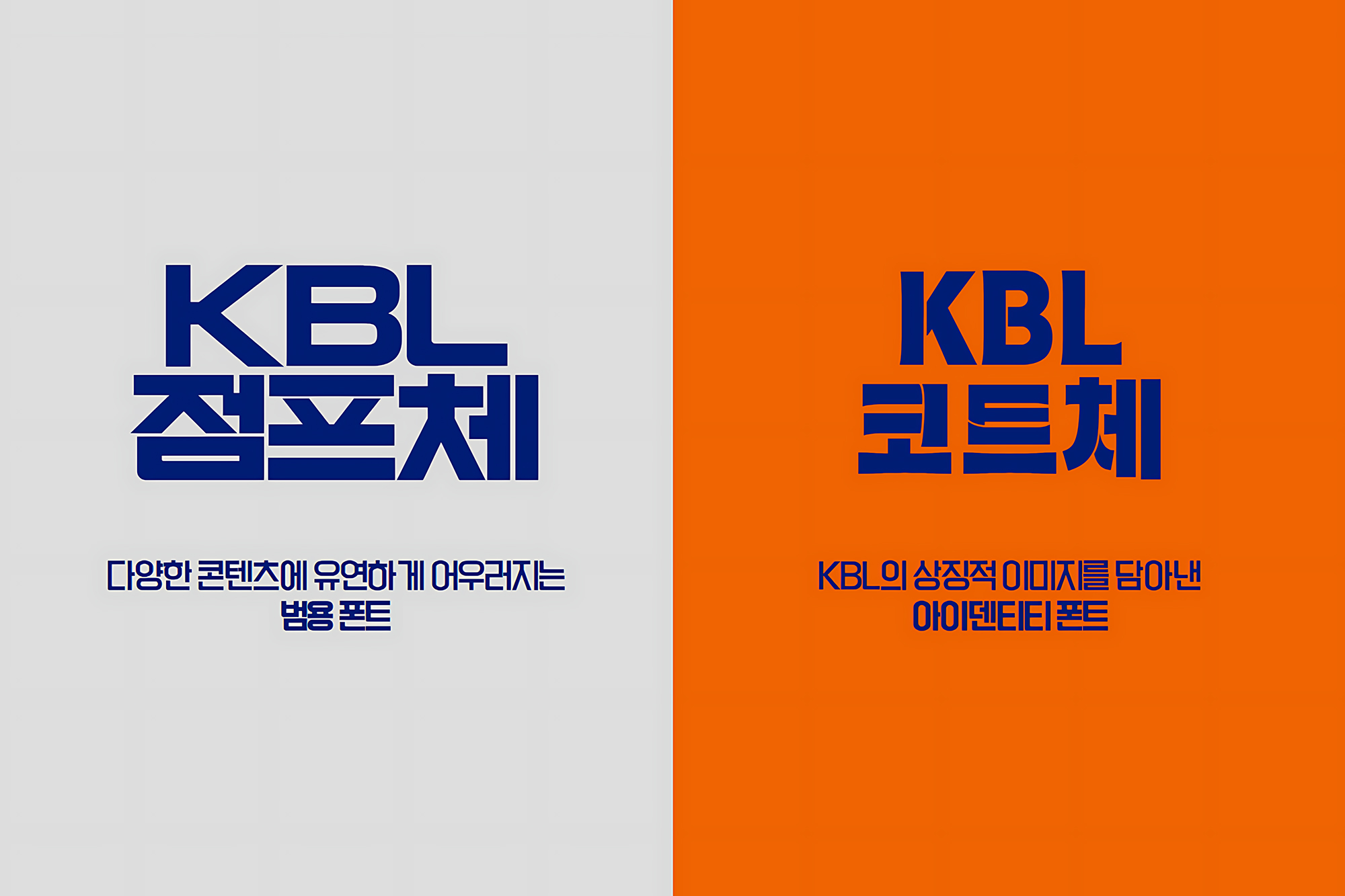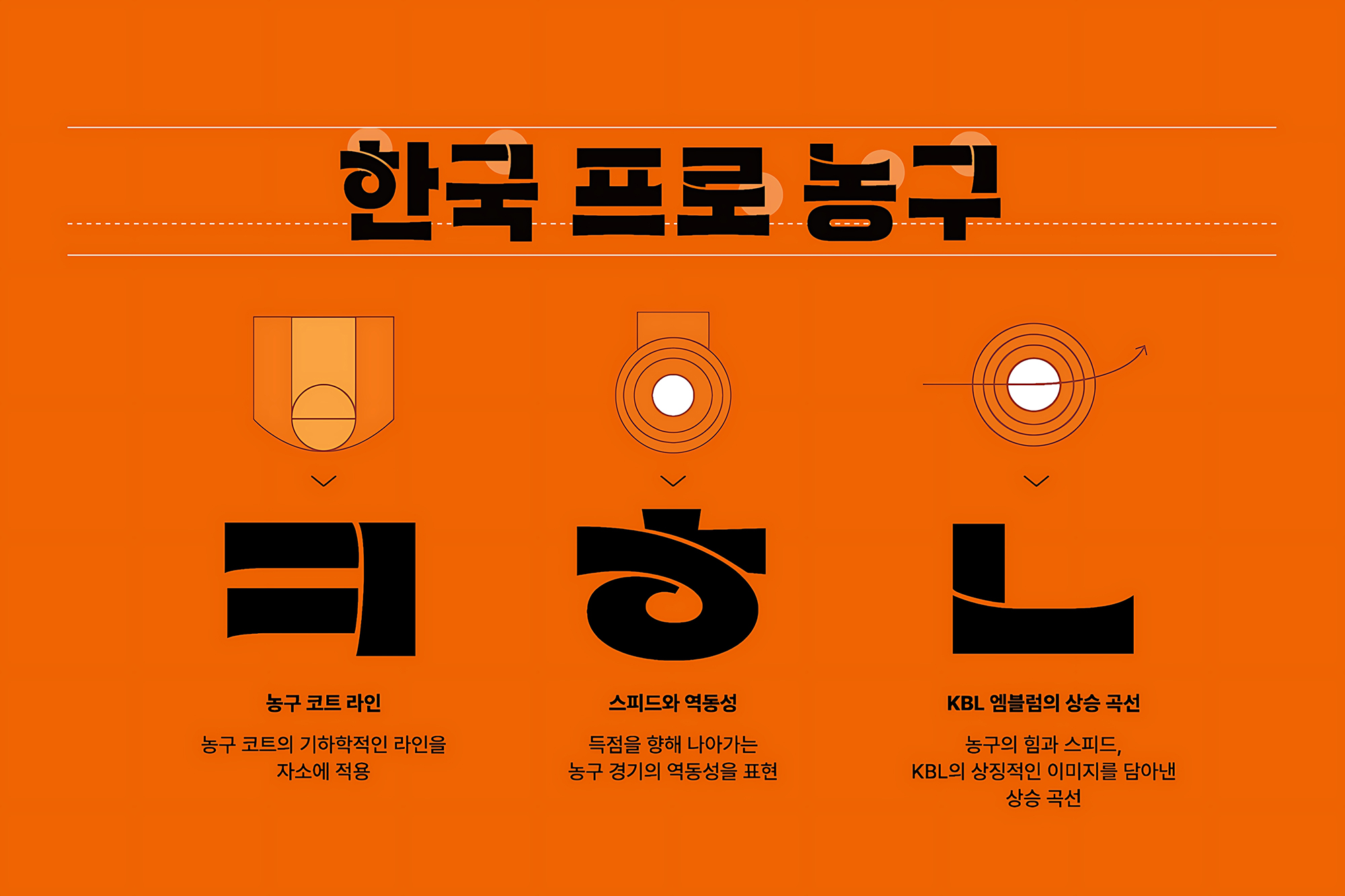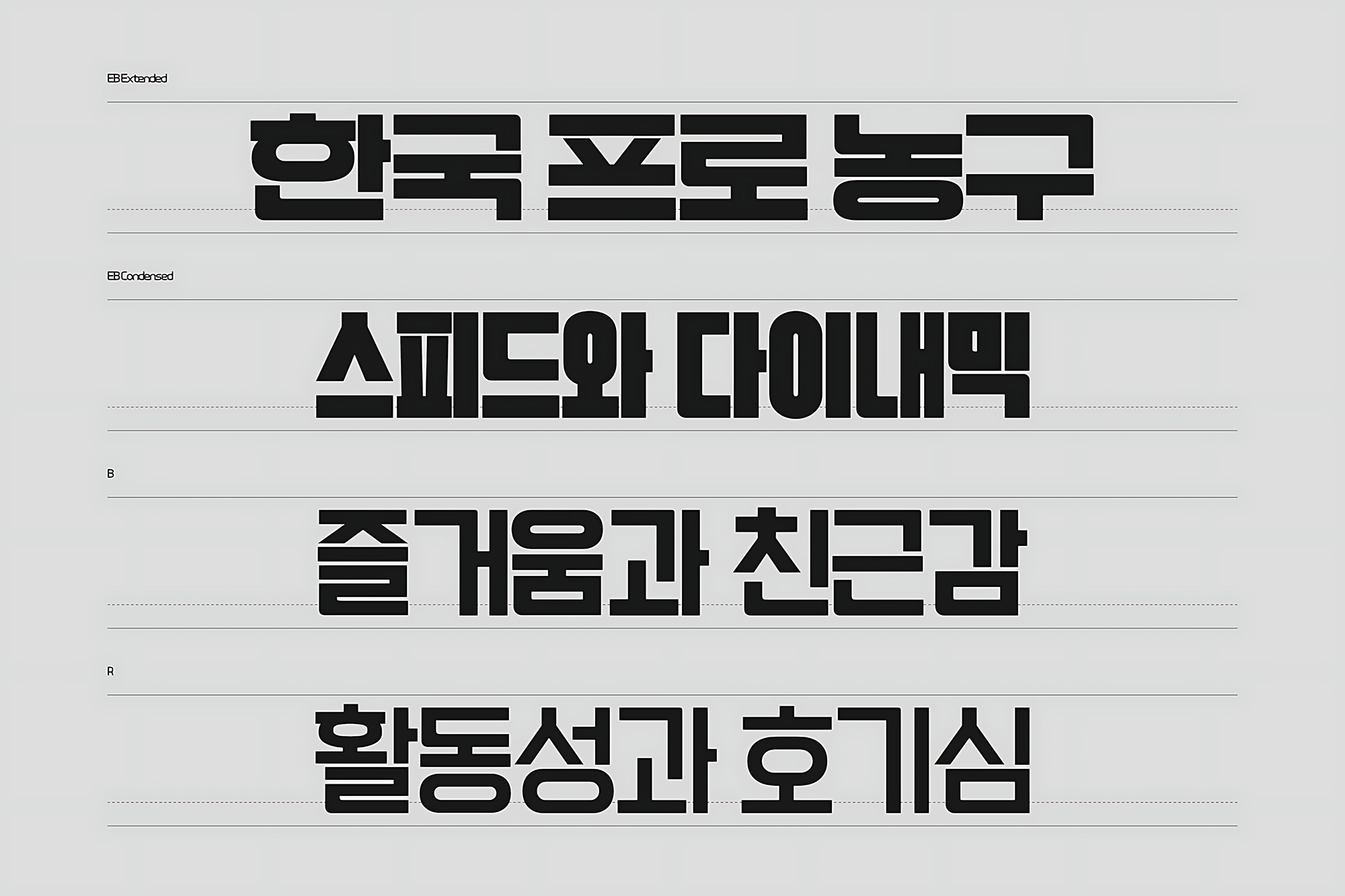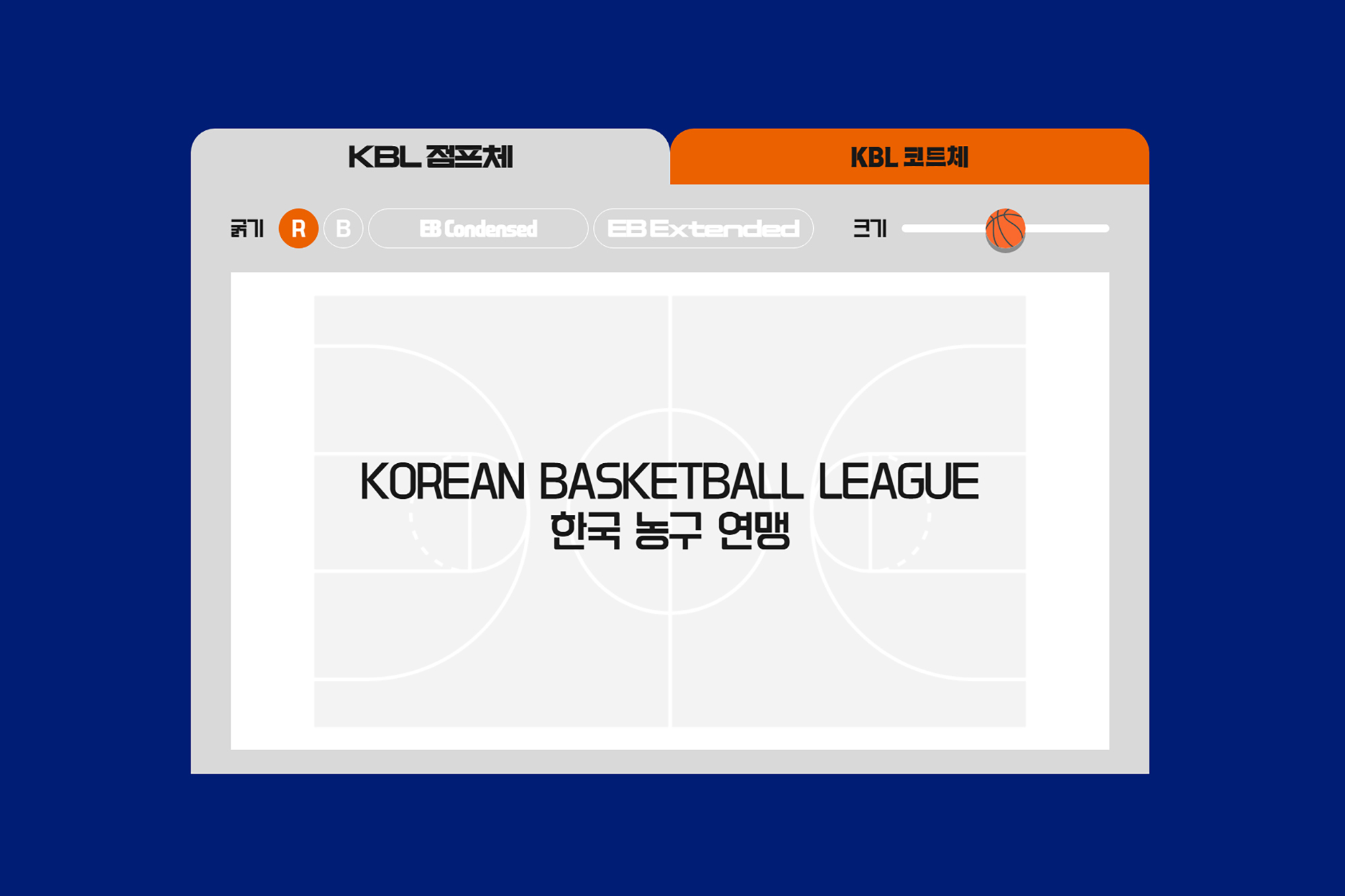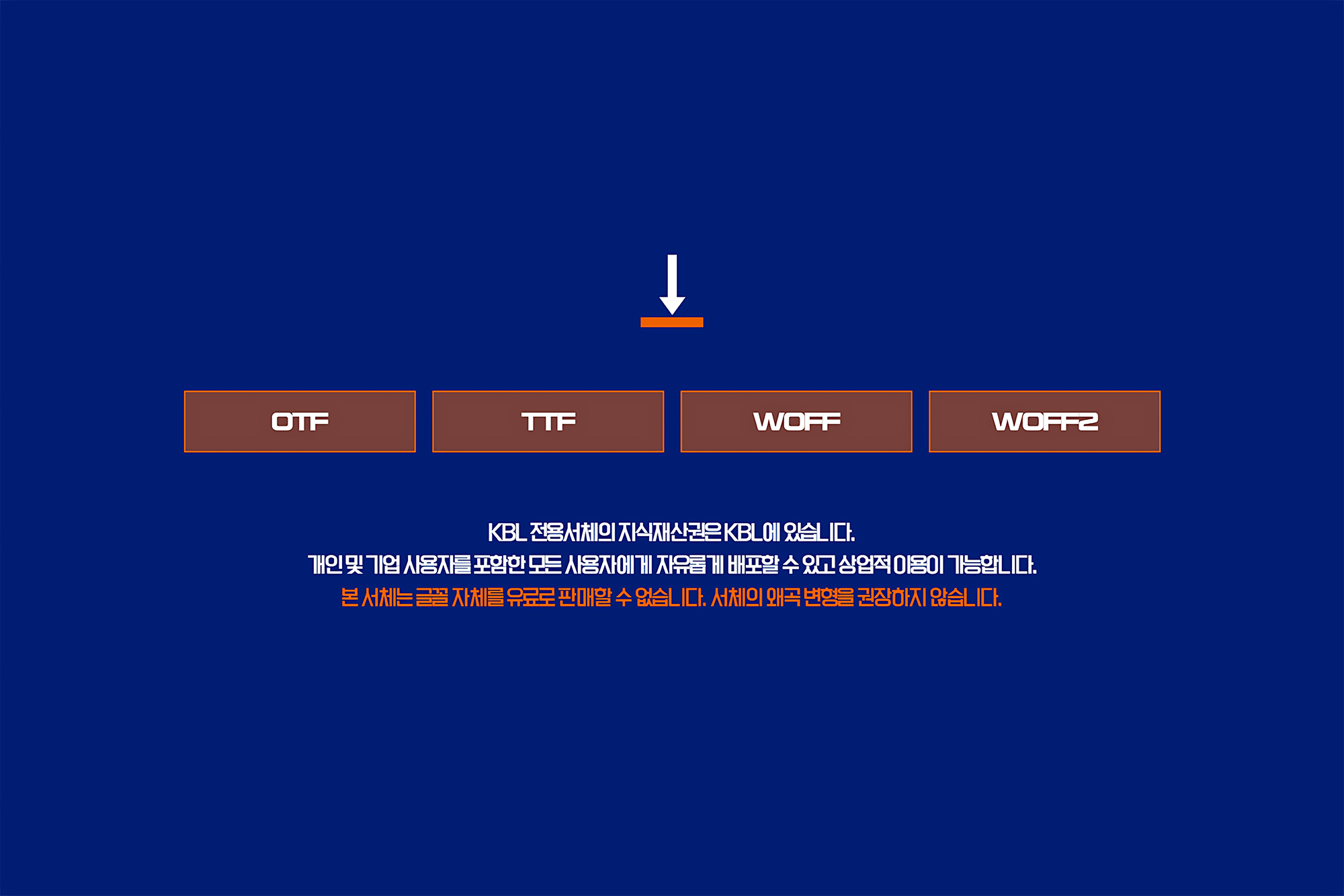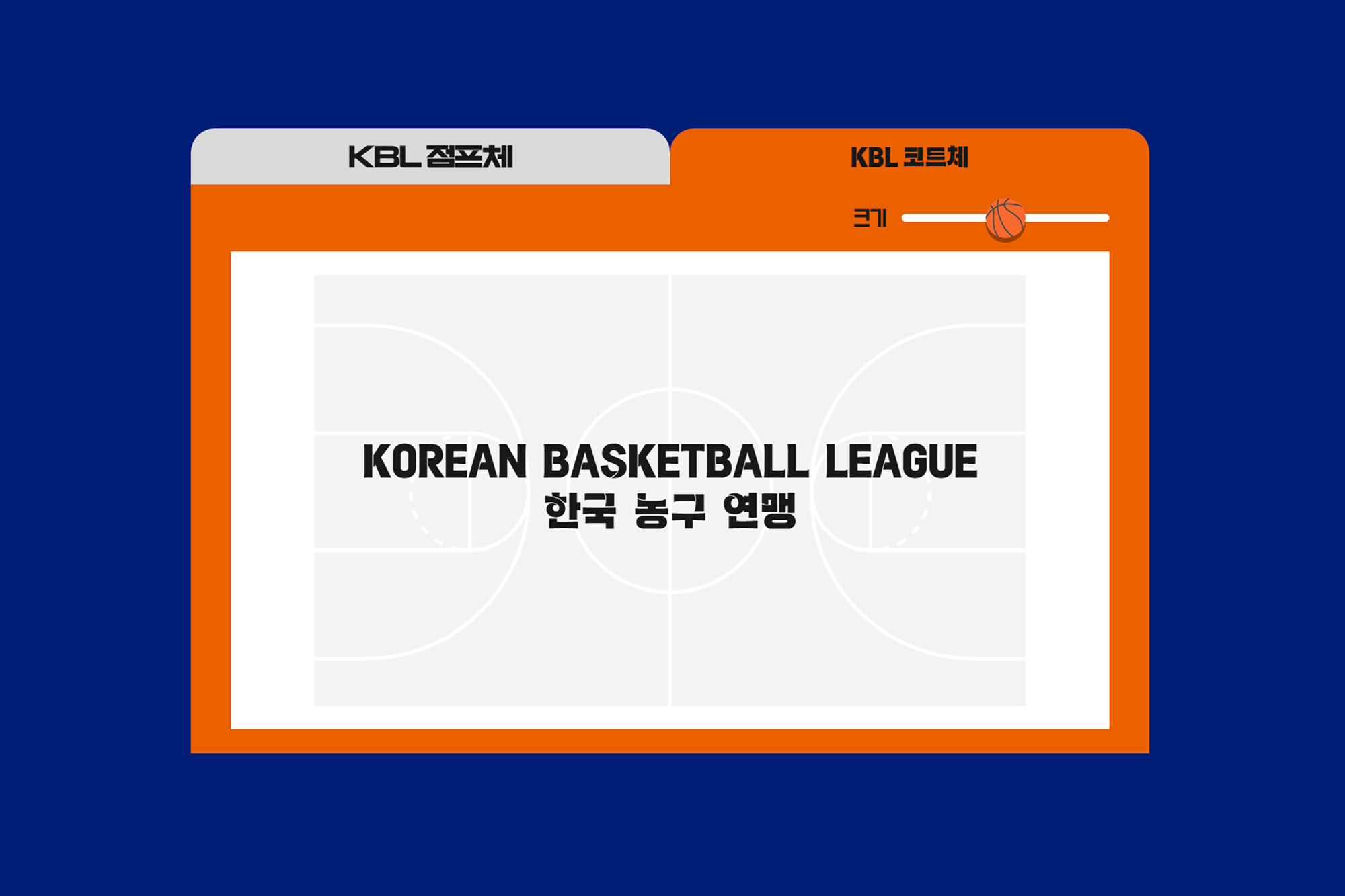
디지털 이미지나 동영상을 제작하다 보면 분위기에 맞는 폰트가 필요합니다. 그런데 상황이 천차만별이기 때문에 가능하면 많은 서체를 모아놓고 상황에 맞춰서 활용하는 경우가 많습니다. 그래서 저는 다양한 배포 폰트들을 모으고 있는데요. 이번에 한국프로농구(KBL)에서 전용 서체를 공개했습니다. 그래서 이번 포스팅에서 특징을 확인해 보도록 하겠습니다.
“두 가지 서체”
KBL 전용서체 서체는 KBL 점프체와 KBL 코트체 두 가지로 구성되어 있는데요. 일종의 범용 폰트와 아이텐티티 폰트로 구분되어 있습니다. 최근에 공개되는 서체들의 일반적인 추세이기는 한데요. 필요에 따라서 활용해줄 수 있다는 장점이 있습니다.
“KBL 점프체”
KBL 점프체는 다양한 콘텐츠에 유연하게 어우러지는 범용 폰트로 제작되었는데요. 굵기는 R, B, EB Condensed, EB Extended 4가지로 구성되어 있습니다. 농구 코트 라인의 선과 원 요소를 모티브로 디자인되었다고 하는데요. 14도 정도 기울여서 사용하면 멋지다고 설명하고 있습니다.
“KBL 코트체”
KBL 코트체는 농구 코트 라인과 스피트와 역동성 그리고 KBL 엠블럼의 상승 곡선을 모티브로 제작된 서체인데요. 디자인이 독특한 편이어서 제목 등의 포인트를 주어야 하는 상황에 활용하면 좋을 것 같습니다.
“KBL 전용 서체”